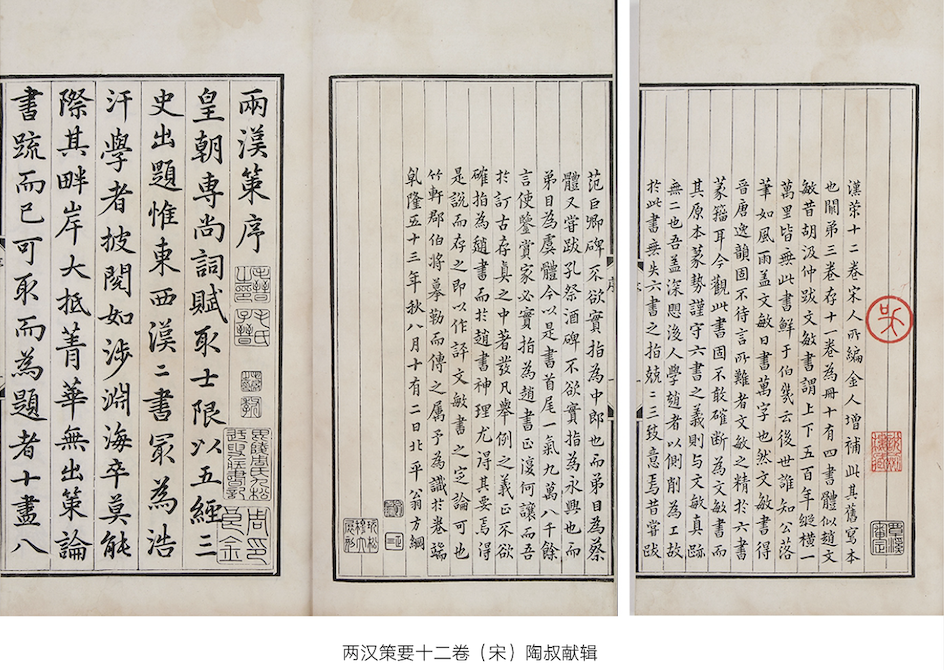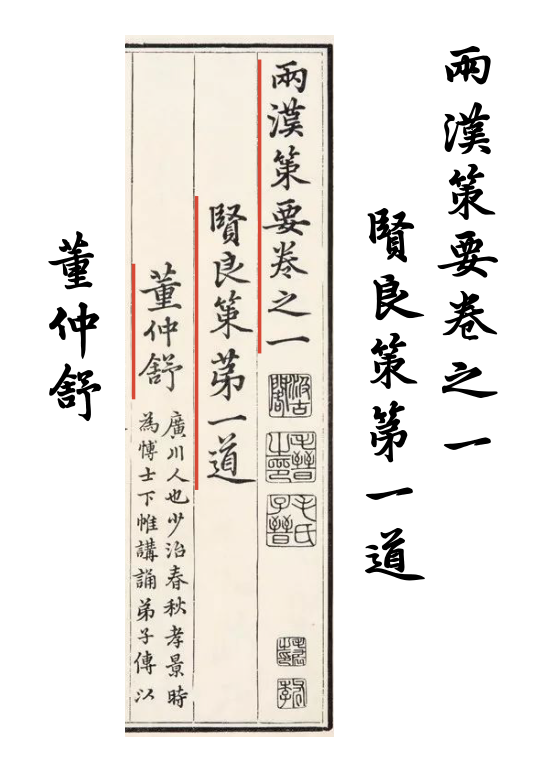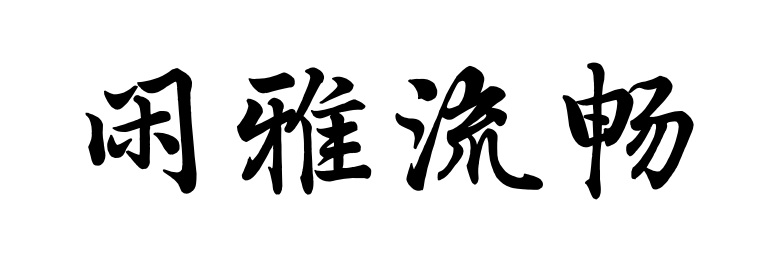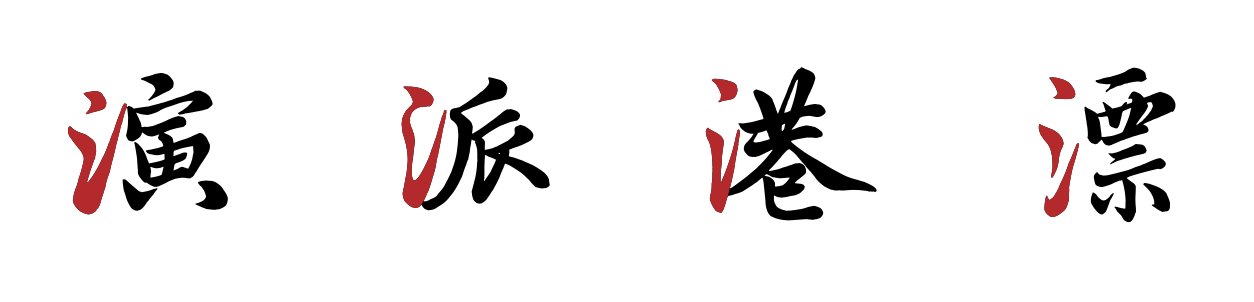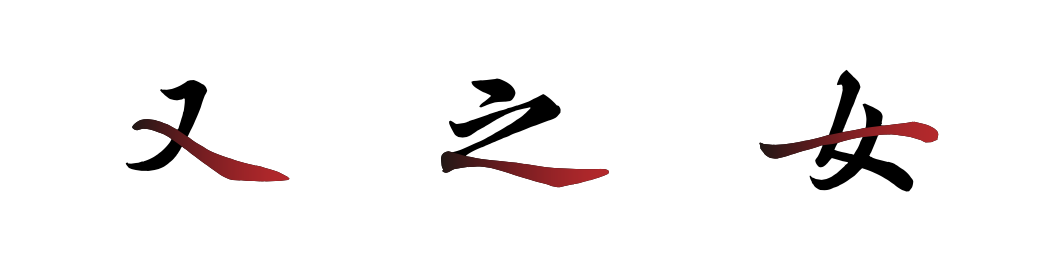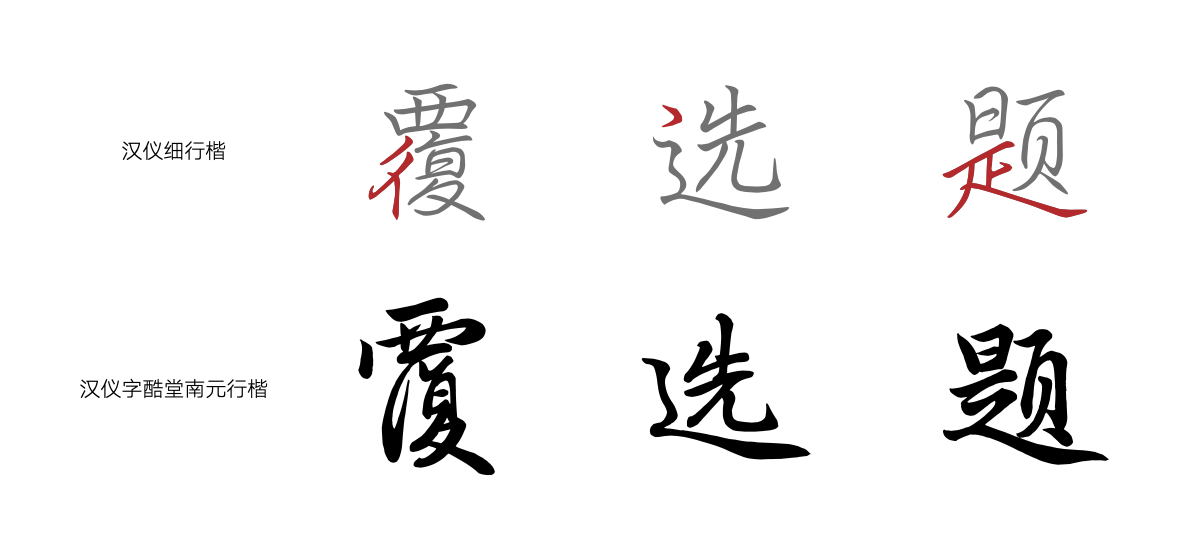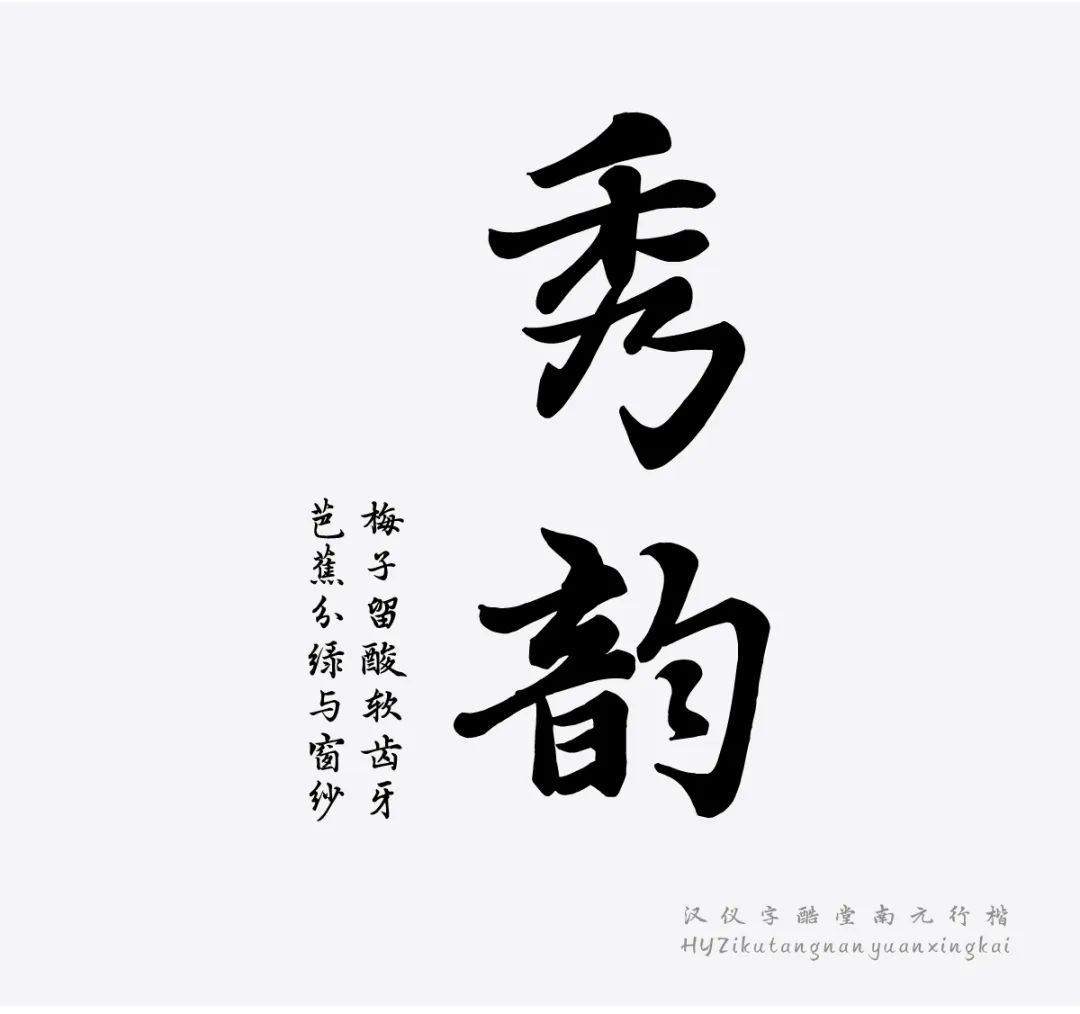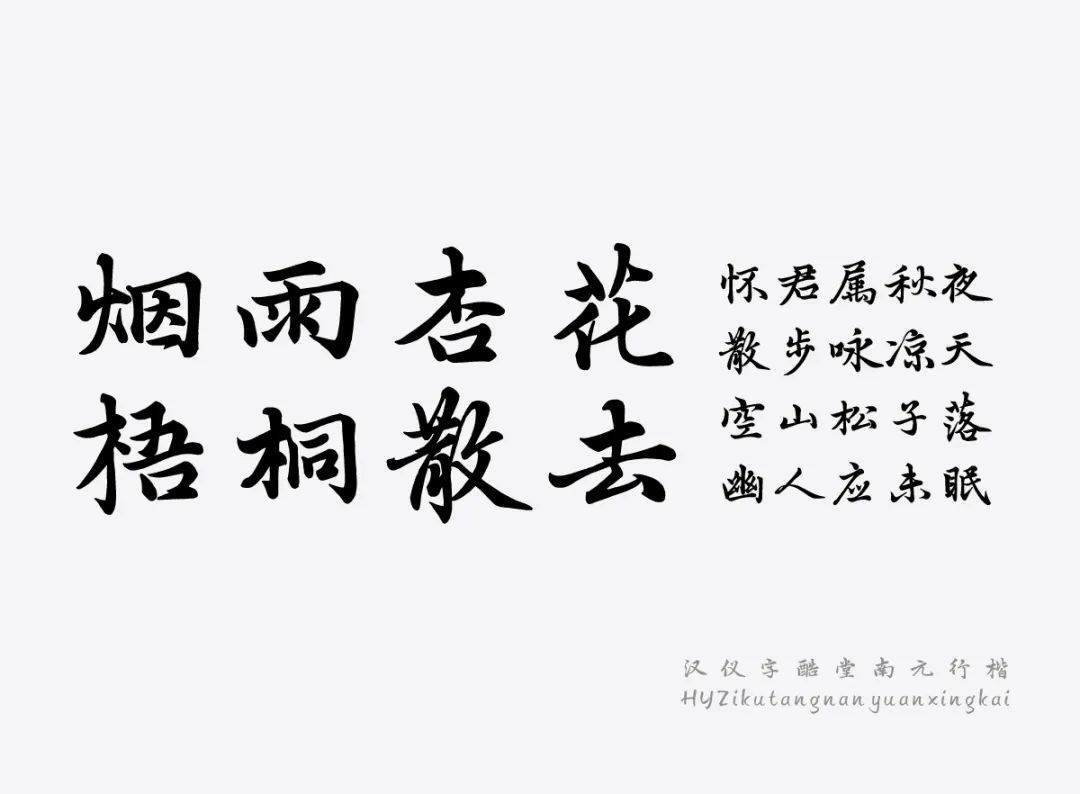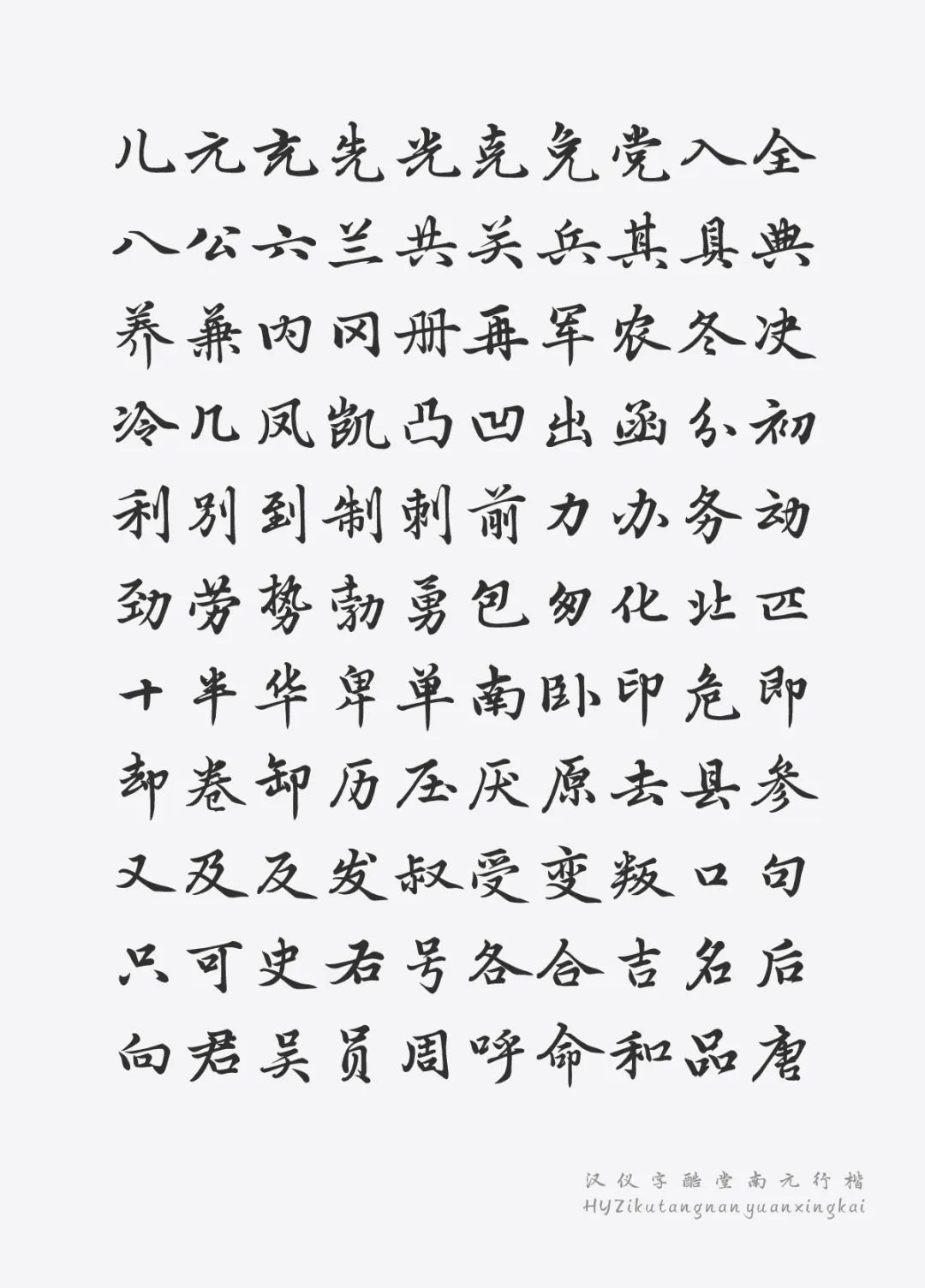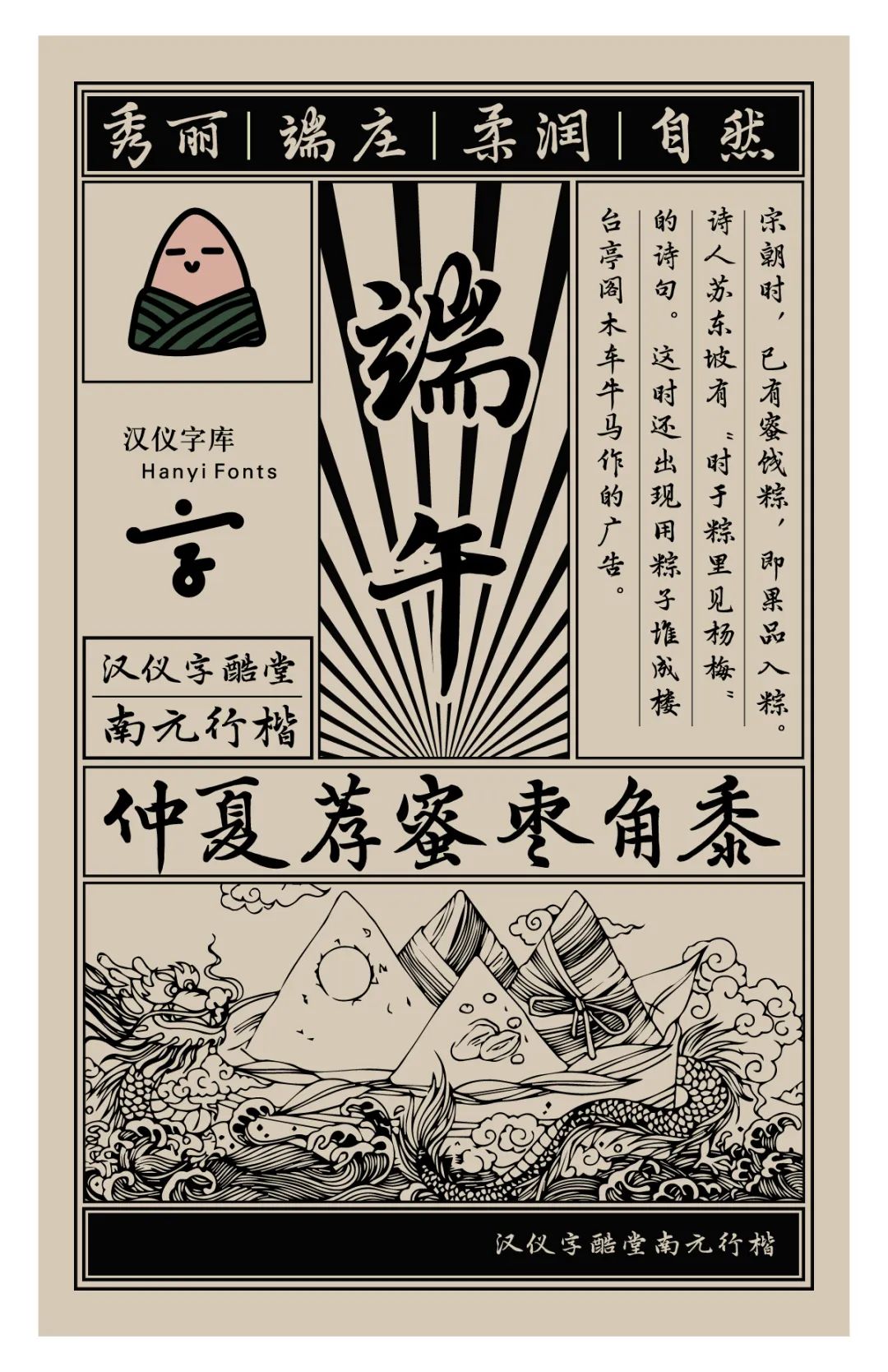
汉仪字酷堂南元行楷
字体来源
汉仪字酷堂南元行楷源自《两汉策要》。《两汉策要》由宋朝陶叔献编辑,收录了两汉期间164篇重要的政论文章,历代盛传为元代书法大家赵孟頫手书。序文后有翁方纲审定评题,称:“不欲确指为赵书,而于赵书神理,尤得其要焉。”现存版本为清乾隆56年(1791)赣郡守张竹轩钩摹影刊元写本。
字体风格
汉仪字酷堂南元行楷作为一款复刻字体,字体工整秀丽,笔法稳健。既保留了唐楷的法度,又不拘泥于唐楷的一招一式,在字体中保留一些生动俊俏的行书笔法与结构,笔划形态生动自然,可从中看到赵孟頫书法的一些风格特征。
字体特点
汉仪字酷堂南元行楷的字形间架方正,结体严谨端庄,重心平稳,布白均匀,点画之间彼引呼应十分紧密。外似柔润而内实坚强,形体端秀而骨架劲挺。
汉仪字酷堂南元行楷的结字自由,字的笔画根据不同连笔位置作出灵活多样性的改变。点画之间多前后呼应,笔意相连。有的甚至干脆就用行书的写法,笔画与笔画之间有牵丝映带。
汉仪字酷堂南元行楷的撇画、捺画以及横画比较舒展,字势横展。笔画腾挪起伏,有曲折之美。
汉仪字酷堂南元行楷为书写简便,将一些字的偏旁部首做了省减和变形,使字体更加流美遒劲、生动活泼。
字体展示